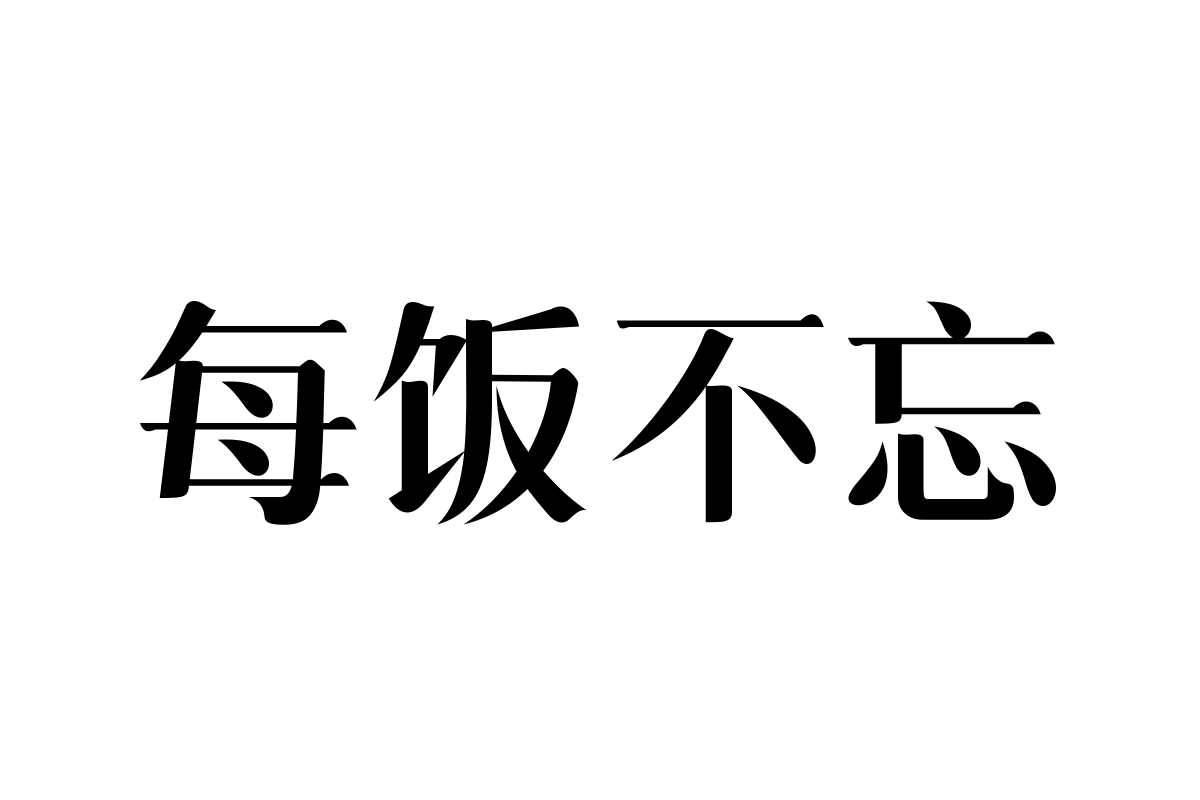
三极清宋简体-中是一种中文字体,主要用于排版和打印。这种字体的特点是字形简洁明了,易于阅读,适用于需要清晰、快速传达信息的场合。
三极清宋简体-中的字体特点如下:
1. 字形简洁:这种字体的字形设计简单,没有过多的装饰和复杂的笔画,使得文字看起来更加清晰易读。
2. 易于识别:由于字形简洁,这种字体的文字具有较高的辨识度,便于读者快速识别和理解内容。
3. 适用范围广泛:三极清宋简体-中适用于各种印刷品,如报纸、杂志、书籍、广告等,能够满足不同场合的需求。
总之,三极清宋简体-中是一种适合用于排版和打印的中文字体,其简洁明了的字形特点使其在各种应用场景中都有很好的表现。